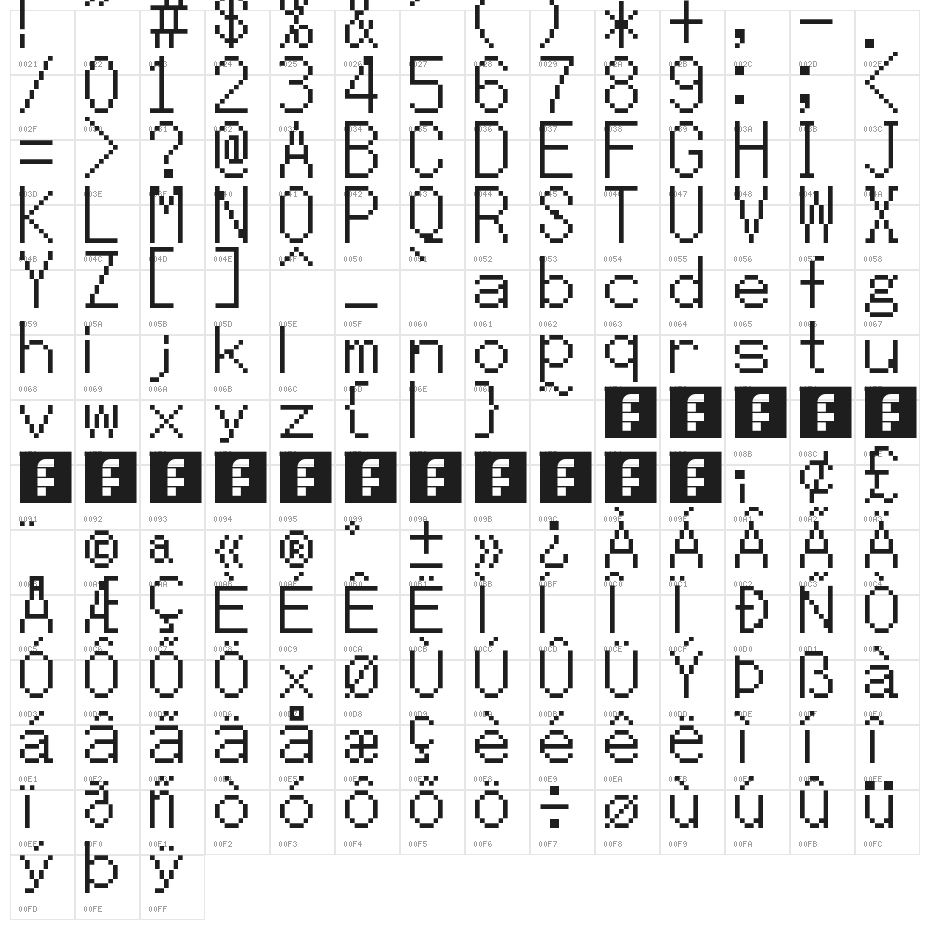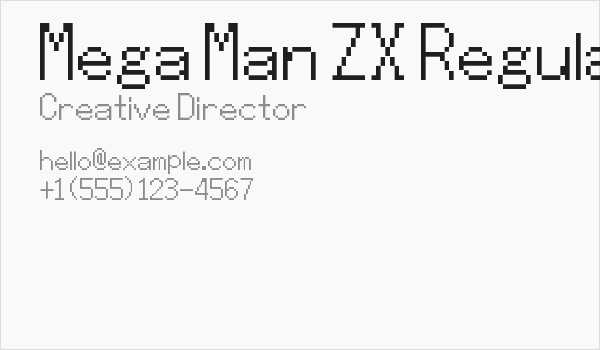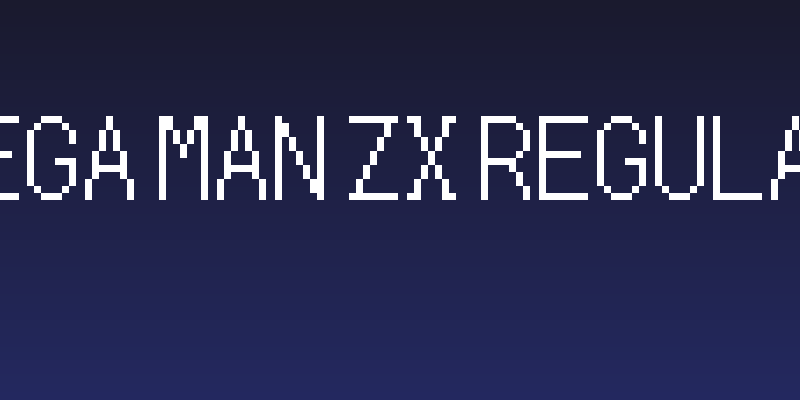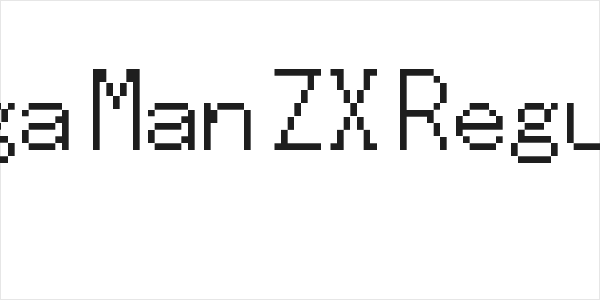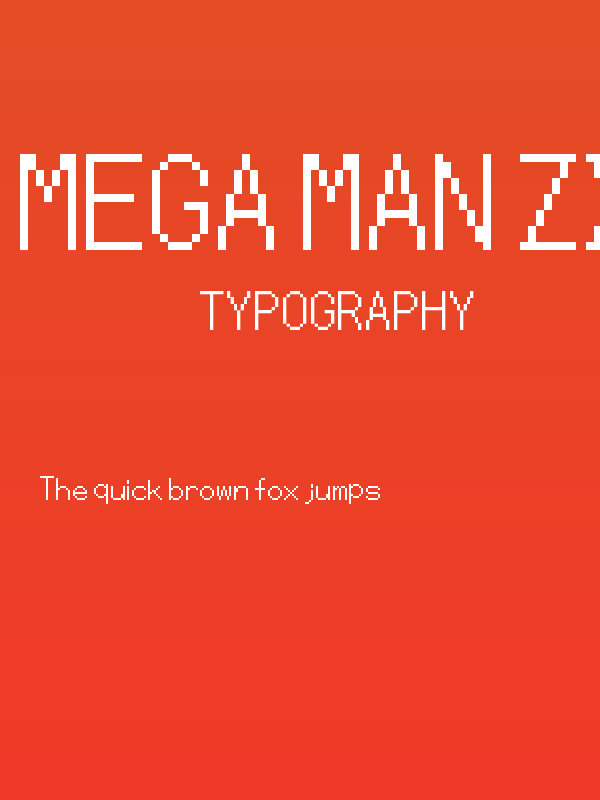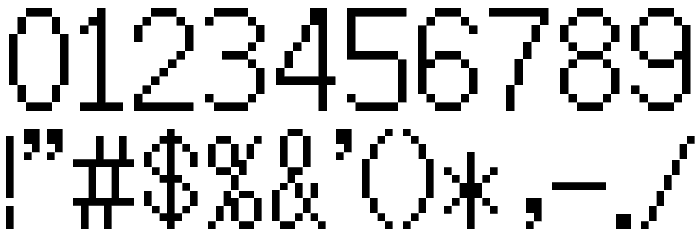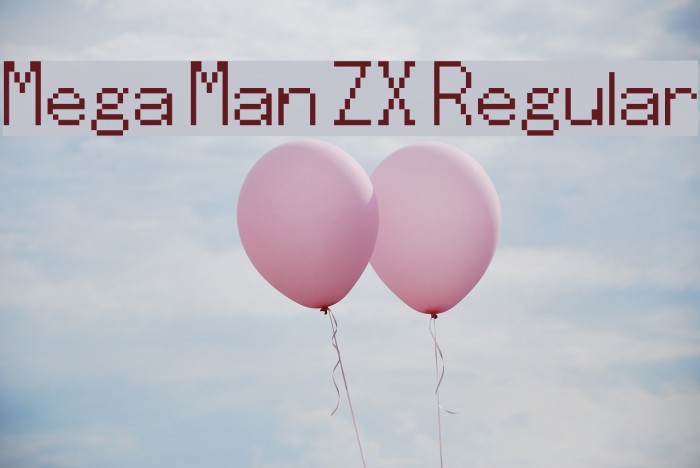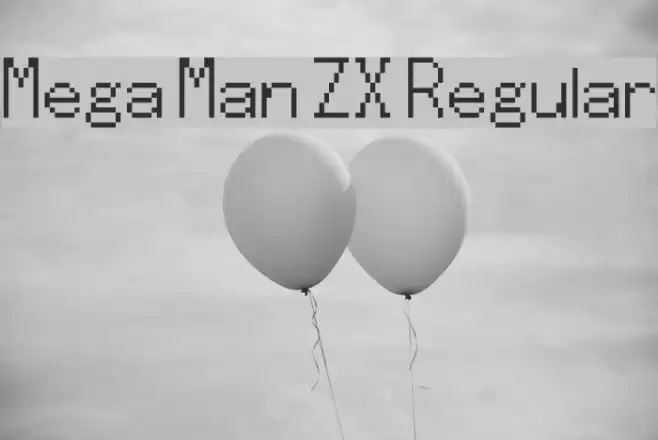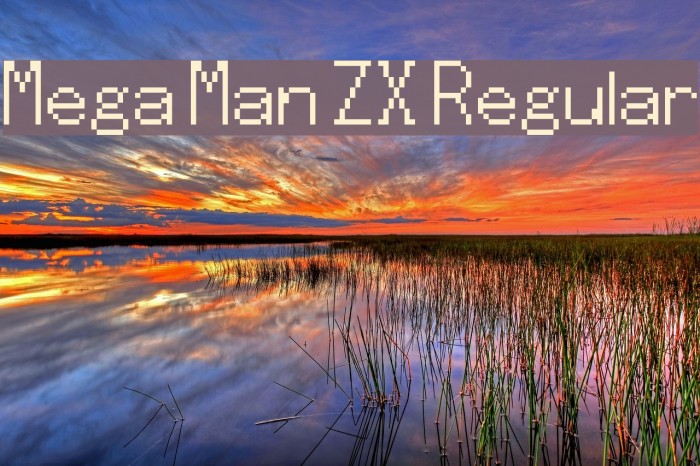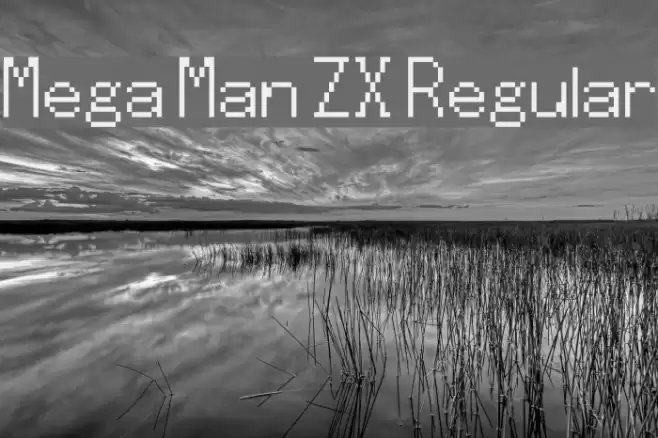
Mega Man ZX Regular Font
✎ Pixel
| 全体的なスタイル | Retro, Digital |
| 用途 | Logos, Digital displays, Video games |
| おすすめプロジェクト | Ideal for video game design, retro-themed graphics, digital art projects, and tech-inspired branding. |